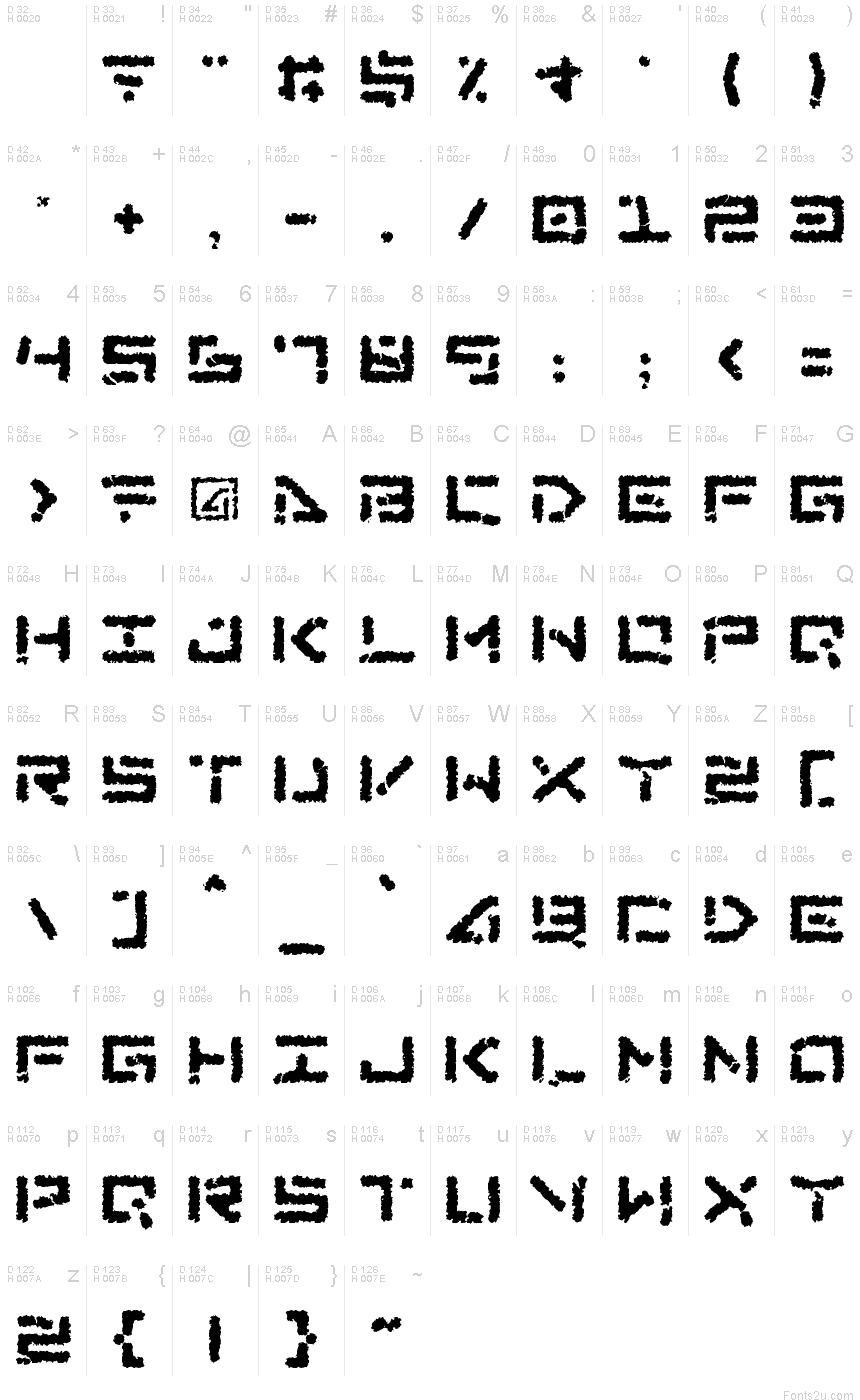
Die Schriftart Abduction III von Rich Gast ist ein kostenloser, verzerrter Display-Font, der wirkt, als wäre er von statischem Rauschen und Schatten zerfressen. Jeder Buchstabe erscheint erodiert und flackernd – wie auf einem defekten Bildschirm oder in Metall eingekratzt – und verleiht Überschriften eine unheimliche, instabile Energie. Der abgehackte, gebrochene Rhythmus der Abduction-Familie lässt Wörter dringend und fast gefährlich wirken, sodass sie auf den ersten Blick Aufmerksamkeit erregen.
Diese kostenlose Schrift glänzt bei Postern für Horrorfilme, Flyern für Geisterhäuser, Branding für Escape Rooms, dunklen Sci-Fi-Covern, glitchigen YouTube-Thumbnails, Spieletiteln und Grafiken für Paranormal-Podcasts. Die raue, körnige Textur kommt groß und fett am besten zur Geltung, da sie die fragmentierten Kanten perfekt betont. Kombinieren Sie sie mit einer klaren, neutralen serifenlosen Schrift für den Fließtext, um das Layout lesbar zu halten, während Abduction III für Gänsehaut und Atmosphäre sorgt.